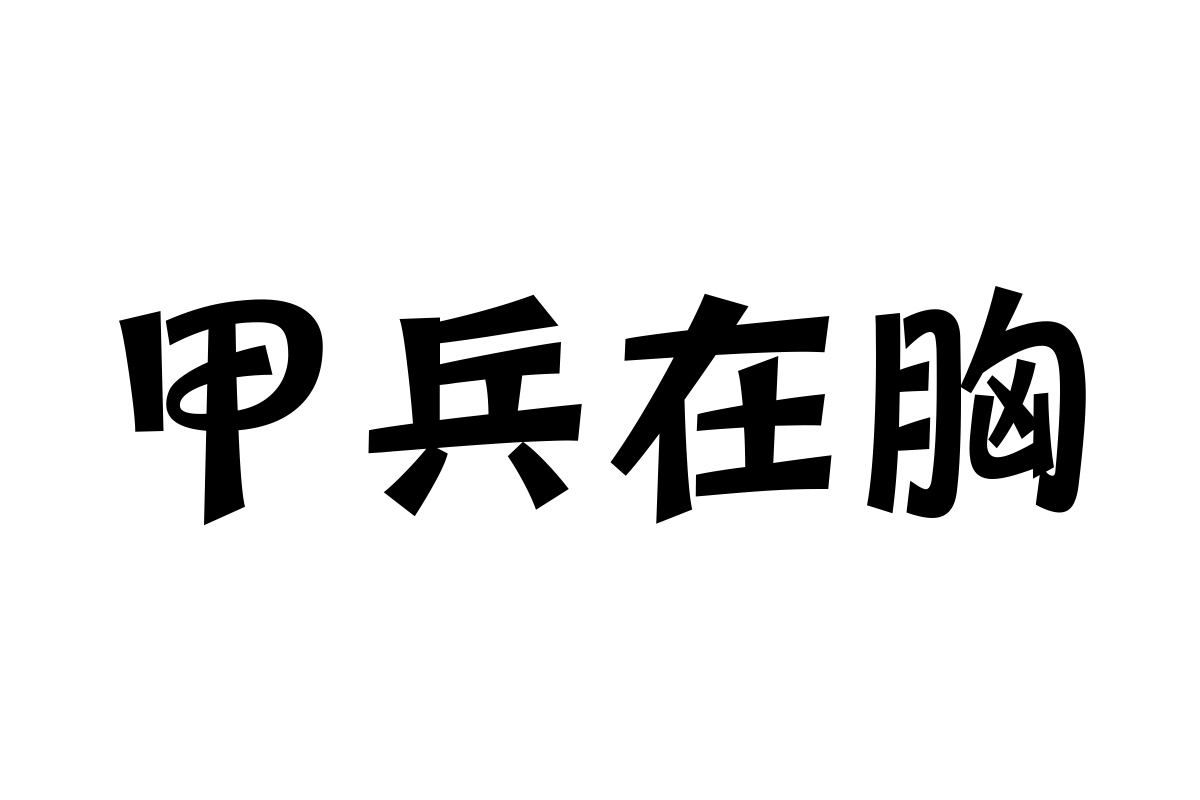
超粗字体是一种用于强调文本的字体样式,其特点是字形宽度较大,笔画粗细明显。这种字体在设计、广告、标题等领域中广泛使用,可以有效地吸引观众的注意力。
超粗字体的特点包括:
1. 字形宽大:超粗字体的字形宽度较普通字体更大,使得文本更加醒目。
2. 笔画粗壮:超粗字体的笔画线条较粗,给人以强烈的视觉冲击力。
3. 易读性高:由于超粗字体的字形和笔画线条较为简单明了,因此阅读起来相对容易。
4. 适应性强:超粗字体适用于多种场合,如标题、标语、广告等,能够很好地传达信息。
5. 个性化:超粗字体可以根据设计师的需求进行个性化调整,以满足不同的设计风格。
总之,超粗字体是一种功能强大且实用的字体样式,广泛应用于各种需要强调文本的场景中。